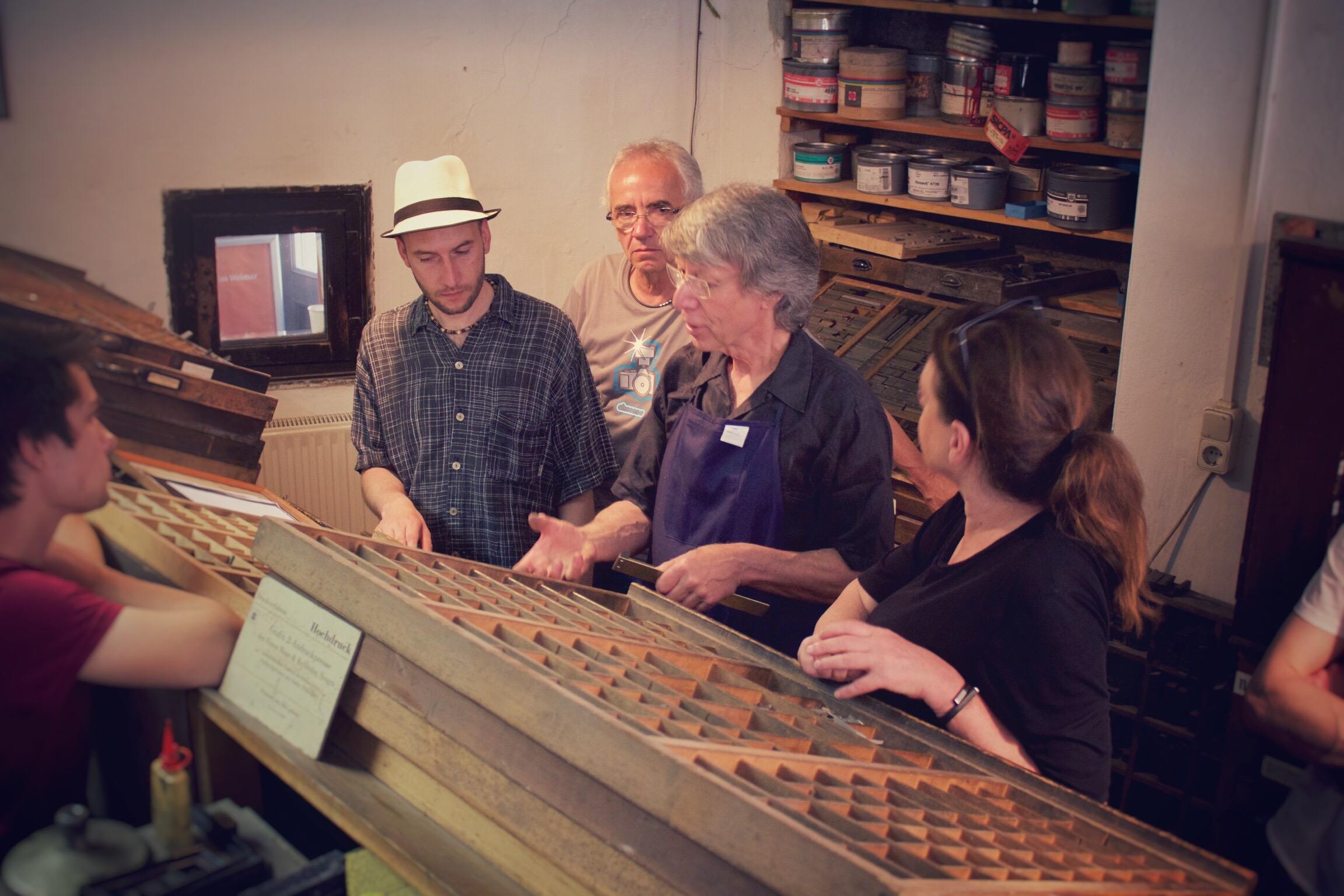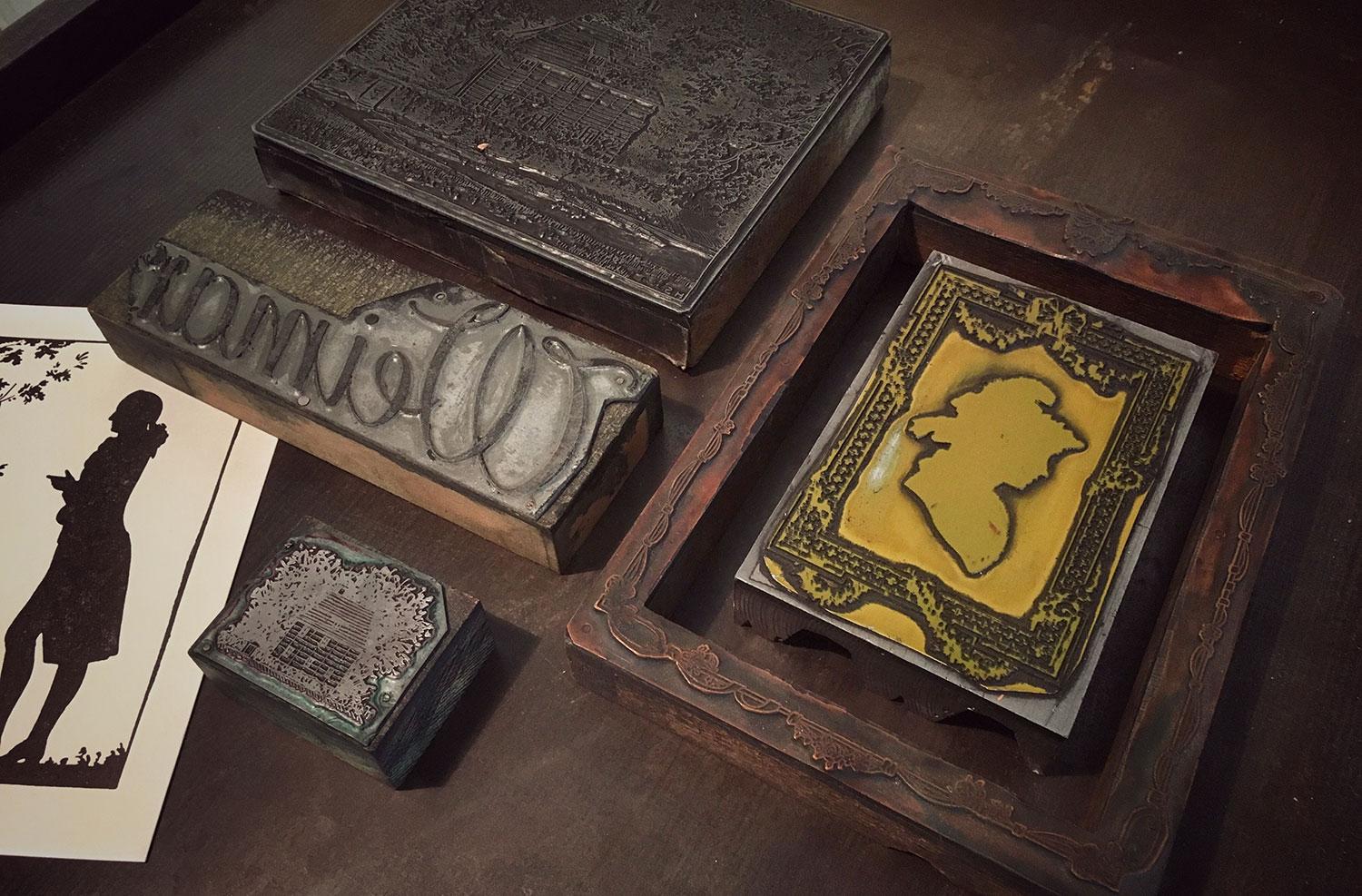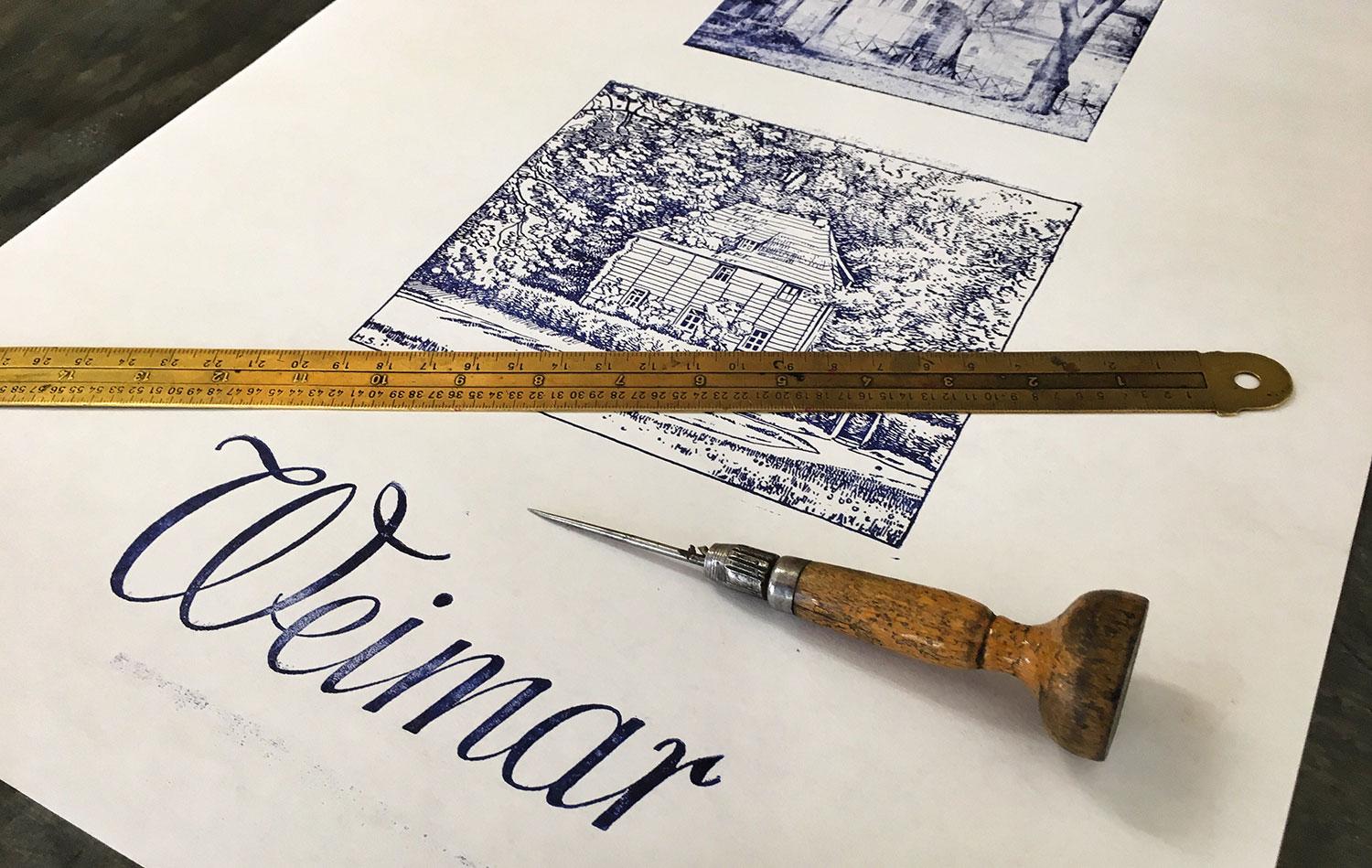
Letterpress-Kurs Weimarer Klassik
Goethe, Schiller, Anna Amalia, Herder, Charlotte von Stein, Wieland … Wir lassen die Zeit der Weimarer Klassik auferstehen und entwerfen mit Klischees, Bleilettern und Schmuckelementen Drucksachen passend zur Goethe-Zeit, die im Anschluss im klassischen Hochdruckverfahren in den Werkstätten der Pavillon-Presse gedruckt und mit nach Hause genommen werden können. Das Team der Pavillon-Presse leitet Sie dabei fachkundig an und führt sie in die über 500 Jahre alte Technik des Handsatzes ein.